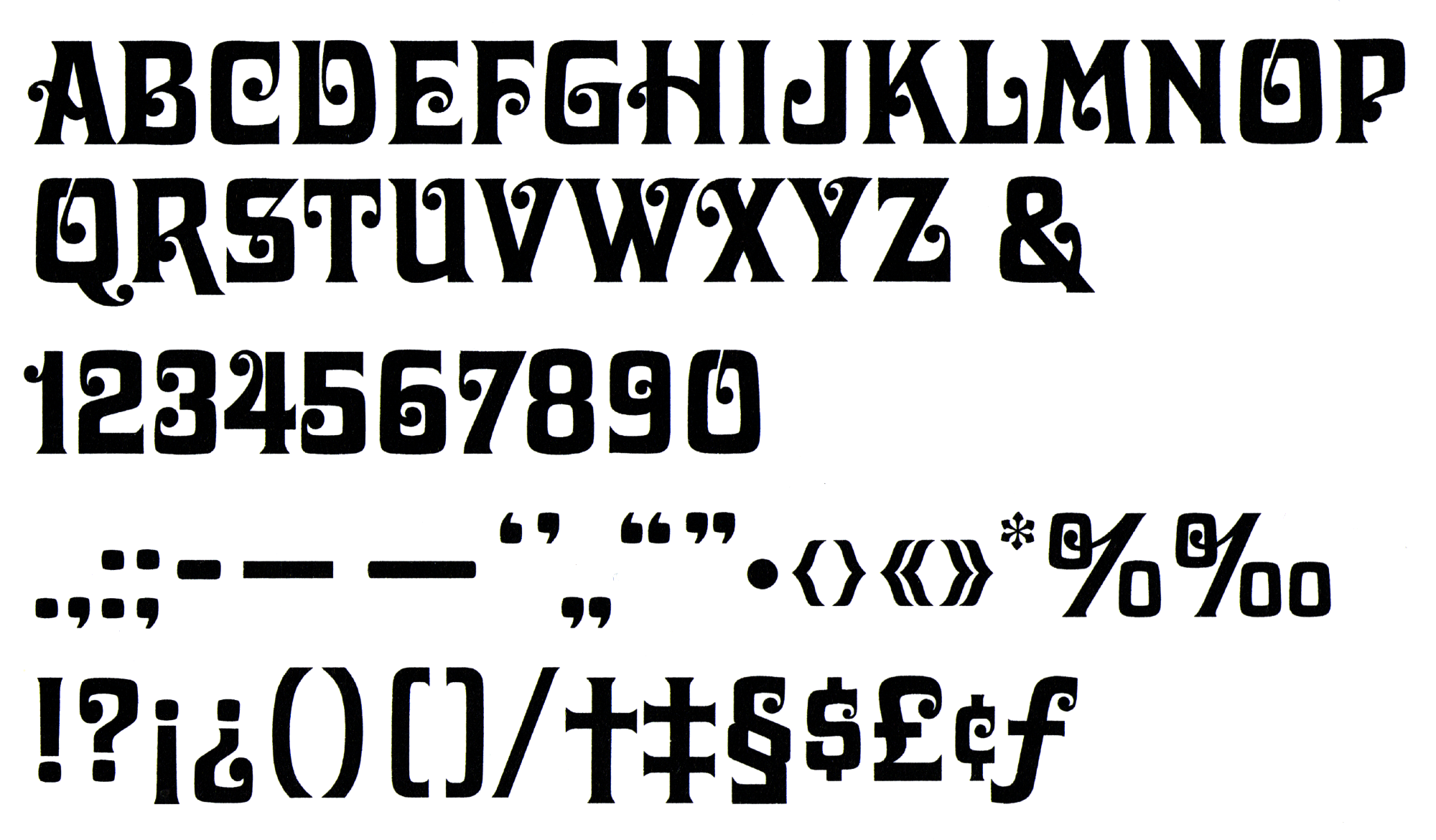
- 1965
- Antiqua dekorativ
Die Davida ist ein Versalalphabet des US-amerikanischen Lettering-Künstlers Louis Minott und erschien 1965 als Fotosatz-Schrift über die Visual Graphics Corporation. Das charakteristische Merkmal sind die betonten Tropfenserifen.
Die Schrift wurde vielfach adaptiert und ist digital von zum Beispiel Bitstream, URW, Linotype, Tilde und Elsner+Flake erhältlich. Eine Neuinterpretation, die Grundprinzipien der Schrift auf verschiedene Schriftgattungen überträgt, ist die Casserole von Ohno Type.